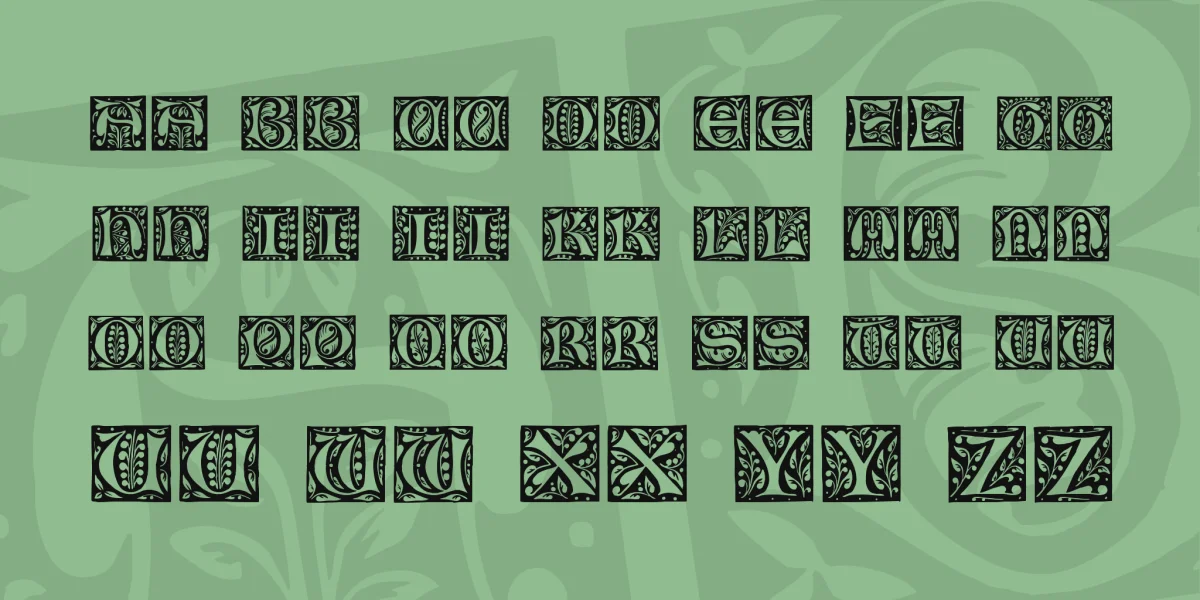
Copyright © Typographer Mediengestaltung, 2002. All rights reserved. Initialen mit Buchstabenformen aus der Gotik. Entstanden um 1850. Digitalisiert durch Dieter Steffmann, Kreuztal.